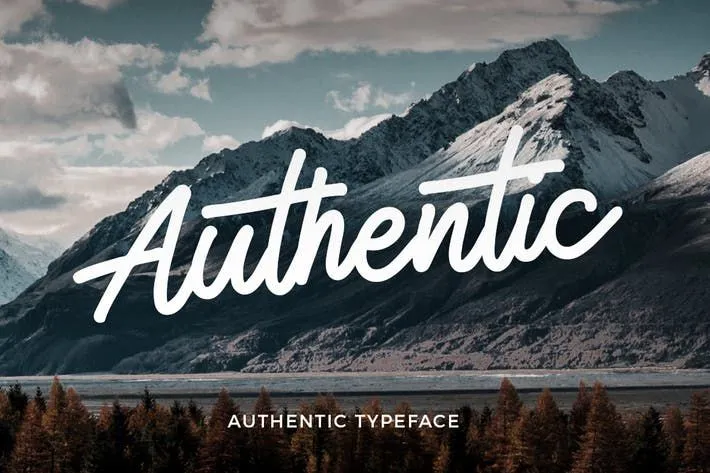
Authentic Monoline Script Font – Download Grátis
Descubra a Authentic Monoline Script Font – uma fonte script que captura as influências das letras vintage enquanto se atualiza com características modernas. Inspirada nos traços rústicos e delicados do calligrafista, essa fonte mantém um estilo fresco e minimalista, destacando-se por sua escrita decorativa e a linha de base dançante que dá ao texto uma sensação vibrante e fluida. Perfeita para designers buscando incorporar sofisticação clássica em designs atuais, esta fonte traz uma mistura única entre o antigo e o novo, criando um visual único e inovador. Seja você um designer de sites ou editor de conteúdo, a Authentic Monoline Script Font é sua escolha ideal para dar um toque especial aos seus trabalhos, tornando-os ainda mais profissionais e arredondados.